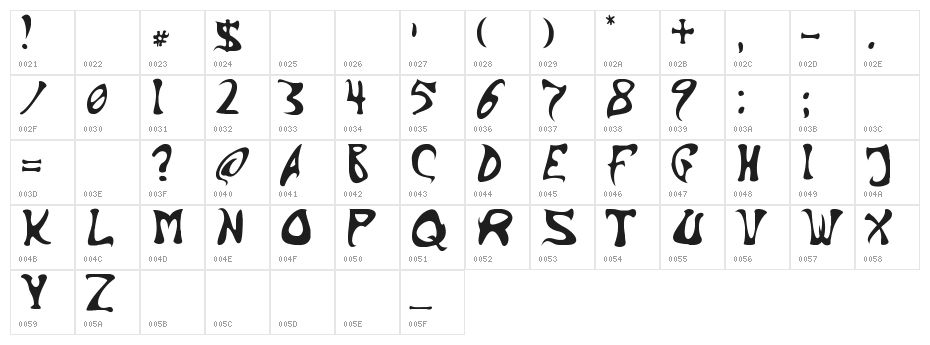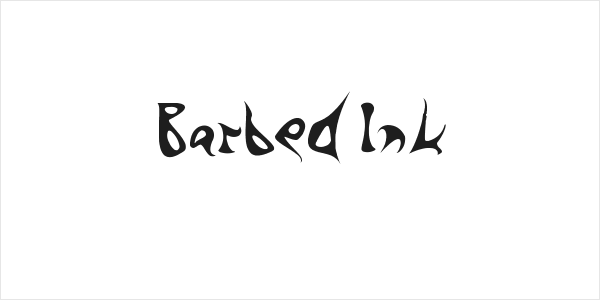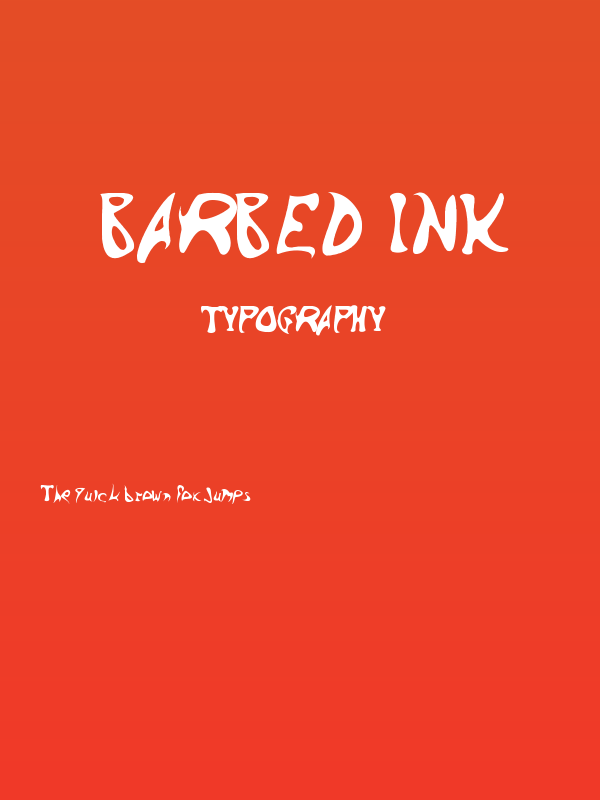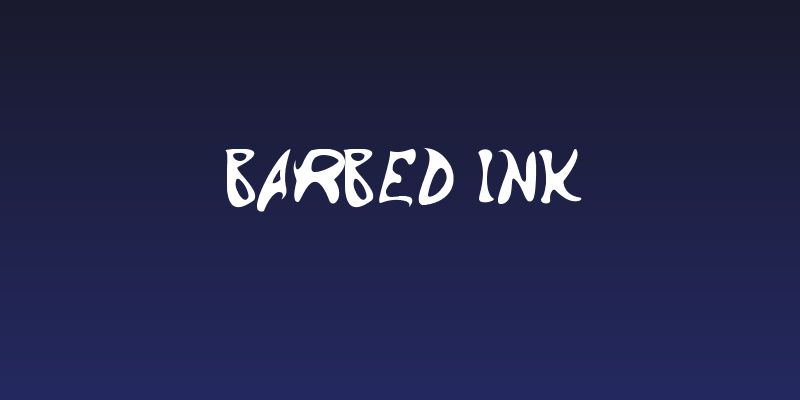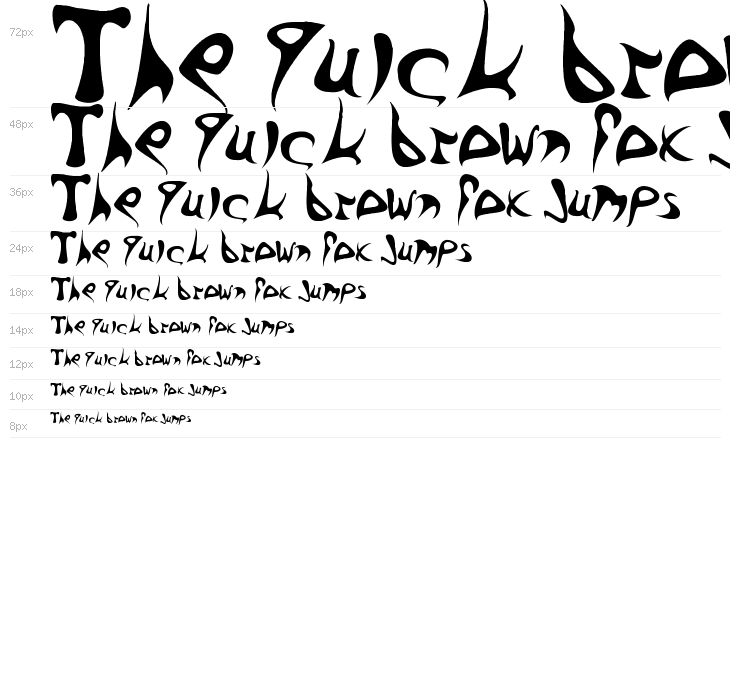
Barbed Ink Font
| Stil general | Modern, Edgy |
| Proiecte propuse | Perfect for album covers, posters, streetwear branding, or any project needing a bold, unconventional look. |